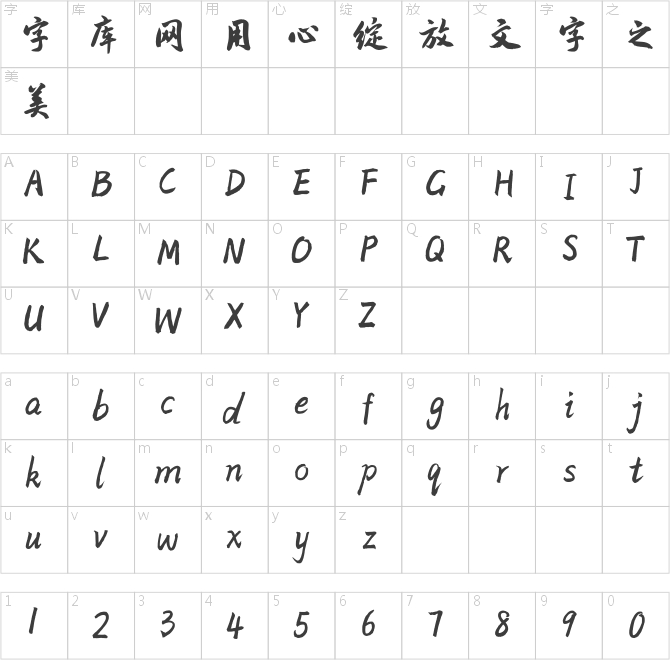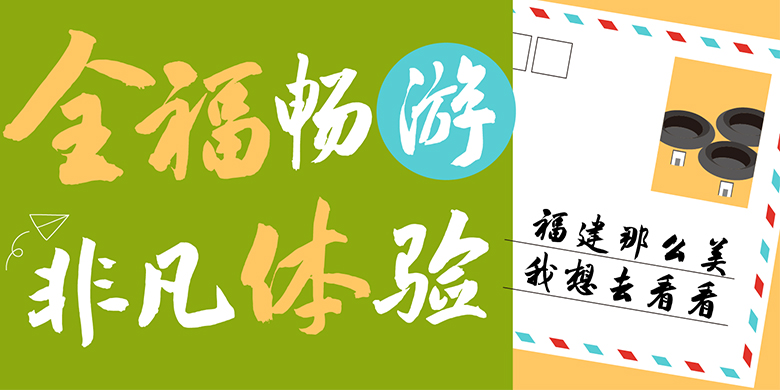
為了更好地塑造福建的區(qū)域形象,體現(xiàn)福建文化旅游資源的豐富性與獨(dú)特性,凸顯“全福游、有全福”品牌,福建省文化和旅游廳與方正字庫聯(lián)合推出福建文旅廳系統(tǒng)專屬定制字體——“全福體”,這是方正首款區(qū)域性定制字體,也是國內(nèi)首款由省級政府文旅管理部門定制的字體。
“全福體”是一款書法行書字體,由來自福建福州的方正字庫設(shè)計總監(jiān)仇寅書寫設(shè)計。“全福體”的設(shè)計,繼承了“全福游,有全福”原始LOGO的厚重和毛筆書寫韻律,受福建山水人文浸潤三十多年的仇寅,在書寫設(shè)計過程中,融合了宋代“尚意”書風(fēng)的格調(diào),并考慮字庫的易識性、通用性,進(jìn)行了多次書寫嘗試及優(yōu)化調(diào)整,最終完稿的“全福體”給人以文雅、厚重、大氣之感,雅俗共賞。
“全福體”將福建獨(dú)特的特征和記憶點(diǎn)融入字體的一筆一畫間,可應(yīng)用于各類傳播媒介和公共空間,在城市形象宣傳和推廣方面都將產(chǎn)生微妙卻不可小覷的影響力。